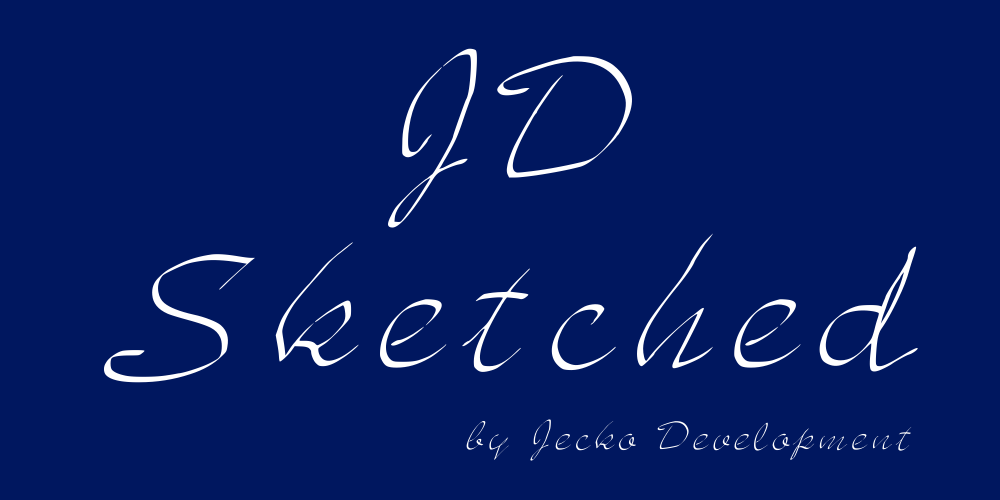
A JD Sketched é uma fonte script criada por Jecko Development em 2015. Desenvolvida com precisão técnica para oferecer textos elegantes e sofisticados, a fonte apresenta um estilo autêntico que combina elementos modernos e tradicionais de forma harmoniosa. Composta pelo designer Hamilton, essa fonte é perfeita para quem busca uma opção única para seus projetos visuais. Seja em design gráfico, arte digital ou criação de identidade visual, a JD Sketched oferece um toque autêntico e sofisticado que complementa qualquer projeto. Engajante e versátil, essa fonte é uma excelente escolha para quem busca uma opção única para seu próximo trabalho. Visite o site da Jecko Development para explorar mais detalhes sobre a fonte e descobrir como ela pode se adaptar ao seu estilo criativo.